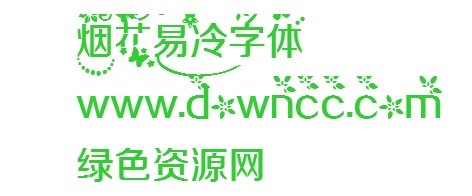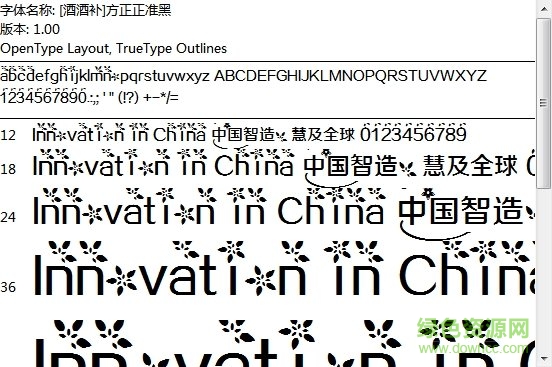
煙花易冷字體是酒酒補充的方正正準黑字體,字體行間充斥著煙花圖案的點綴和紋路,給人一種繁華而熱鬧的視覺體驗,讓文字更加深沉可愛起來,喜歡的朋友就來綠色資源網(wǎng)試試吧!
煙花易冷字體有著十分出彩的視覺效果,讓文字充滿了煙花氣息,給人雋永、華麗的韻味,可以廣泛使用在包裝設(shè)計、平面設(shè)計等場合,是一款活潑動人的藝術(shù)字體!